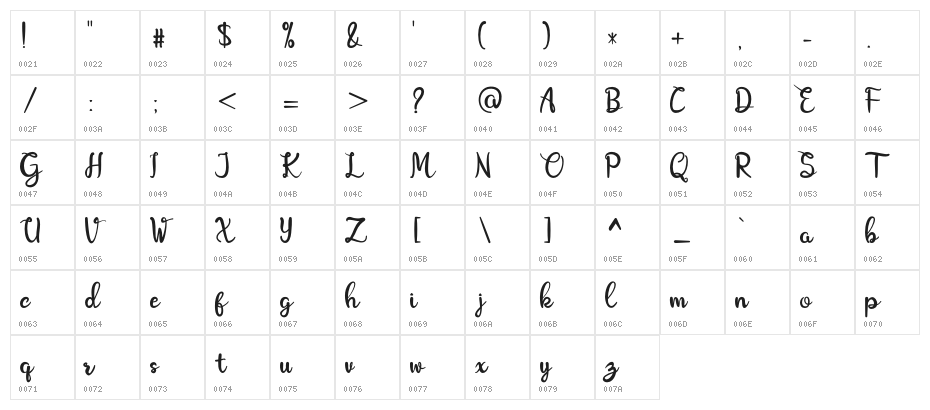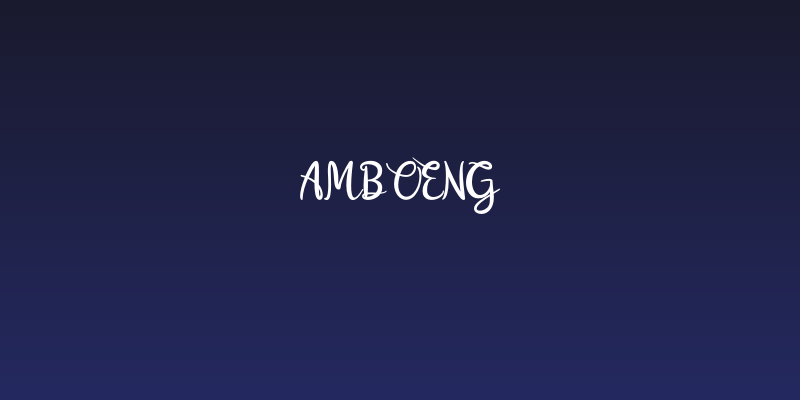
Amboeng Font
| Caso d'uso | Logos, Invitations, Greeting Cards |
| Progetti proposti | Ideal for greeting cards, invitations, personal branding, and creative projects that require a friendly and artistic touch. |